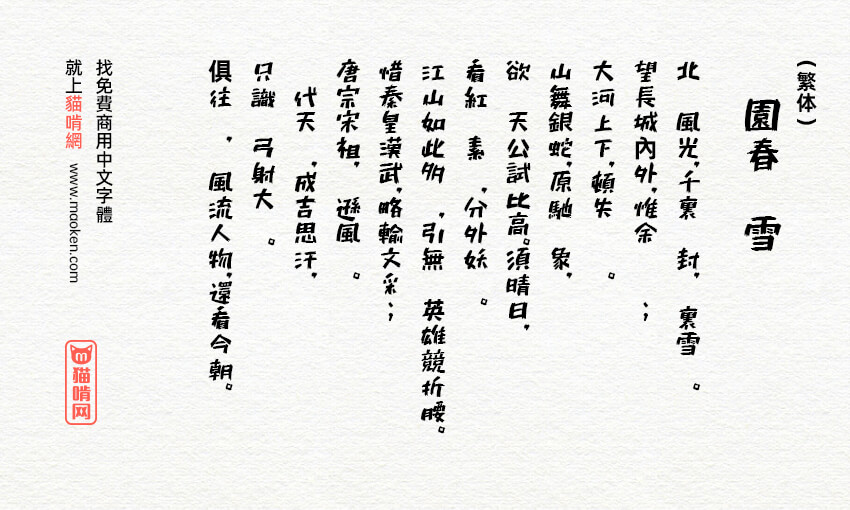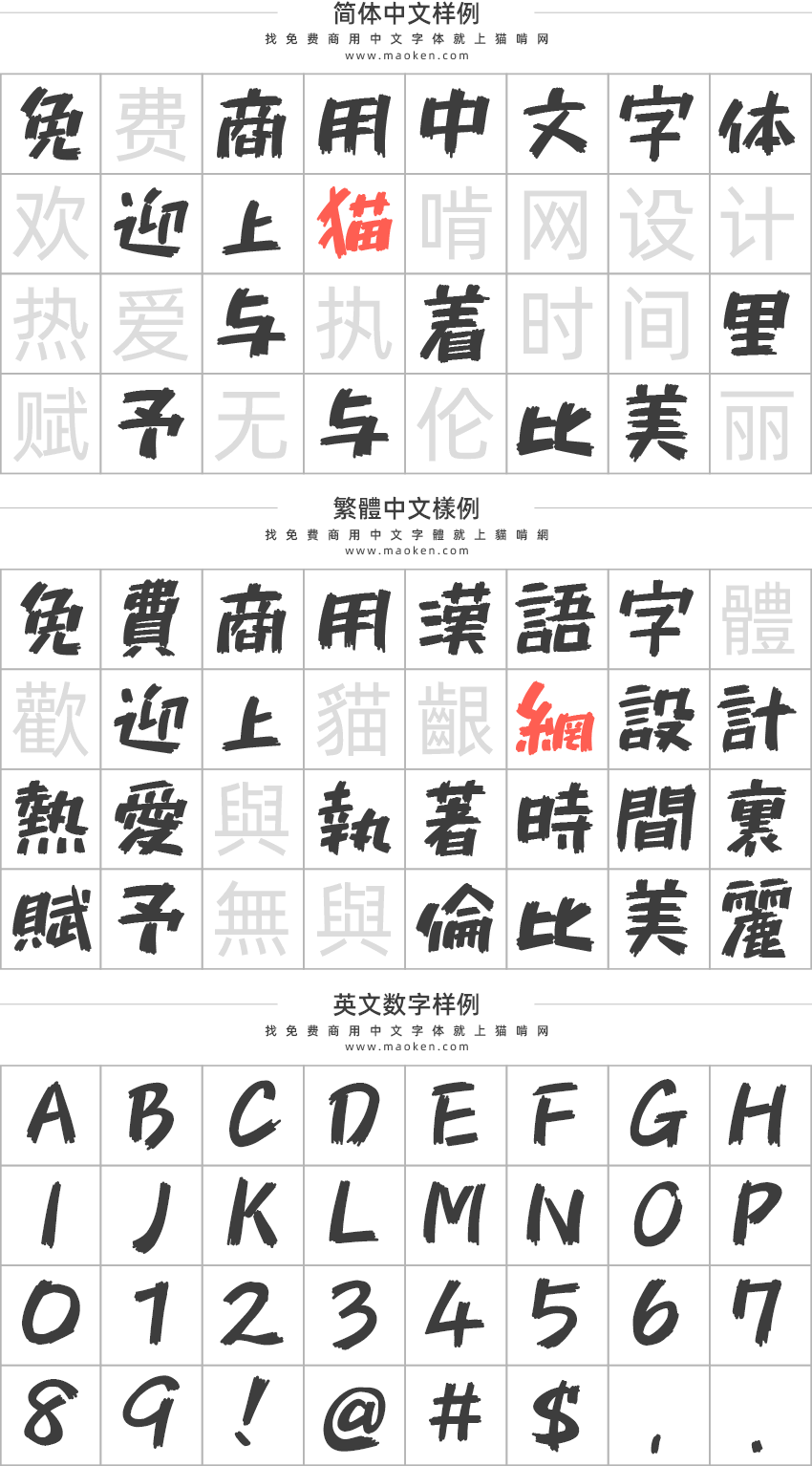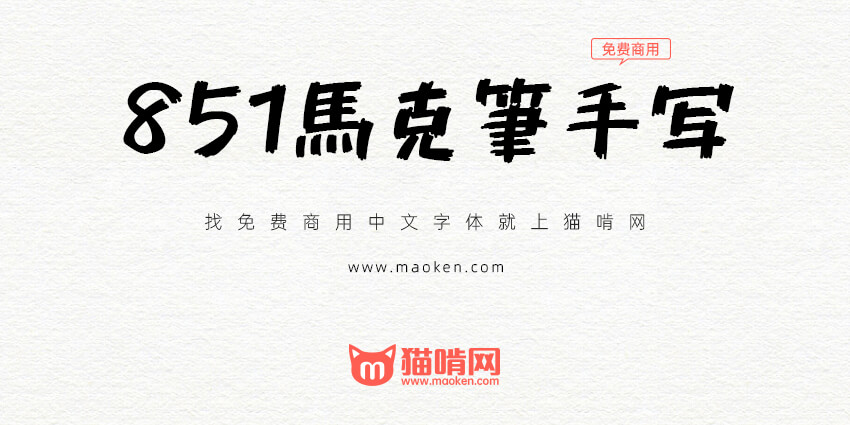
851马克笔手写体:一款十分漂亮的日系免费商用手写字体
851马克笔手写体(日文名:851チカラヅヨク)是日本设计师 8:51:22 pm 设计的字体。这个设计师名字挺有个性的,估计是在这个时间点发生了一件令他印象很深刻的事吧。不管怎么说,他的分享精神还是令人十分敬佩。他已经发布了好几款可以免费商用的字体,本站之前已经介绍过。851手写杂书体,851麻花POP体,等等。
这款马克笔手写体,横细竖粗,行笔飘逸,给人一种吐槽时的动画字幕的印象。不过暂时来说,支持的中文字符不算太多,要使用这一款字体还是要看运气了,如果有刚好需要的字体,还是很不错的,希望作者能补充更多中文字符。
• Shift-JIS符号类·希腊文字·基里尔文字收录完成
• 稍微增加汉字:JIS第1水准收录完成+追加几十个文字
• Ver0.01的平假名复活,开始作为其他版本分发
• 稍微增加汉字:JIS第一水准:2399/2655文字
• 整形平假名
• 添加字母
• 全部对应常用汉字
• 851马克笔手写体(日文名:851チカラヅヨク)第一版正式发布。